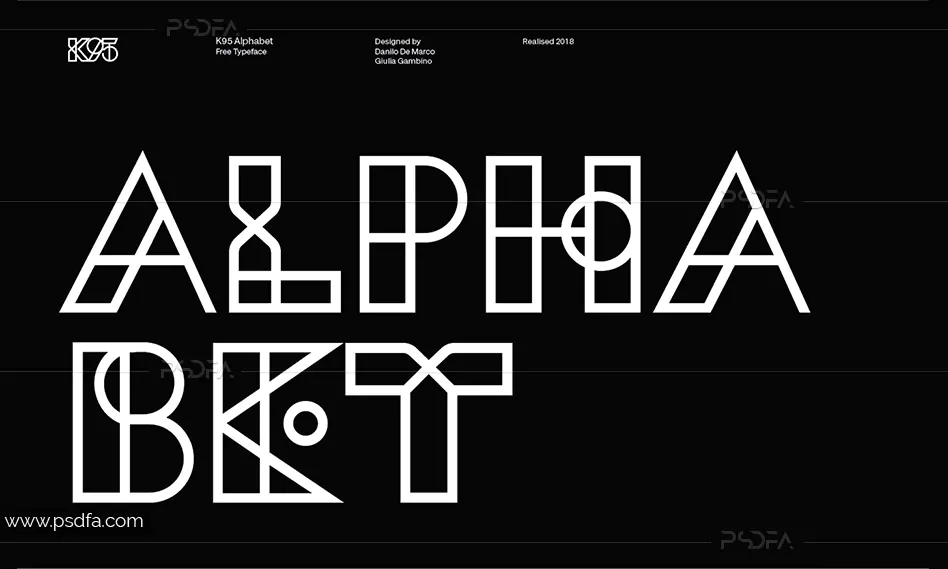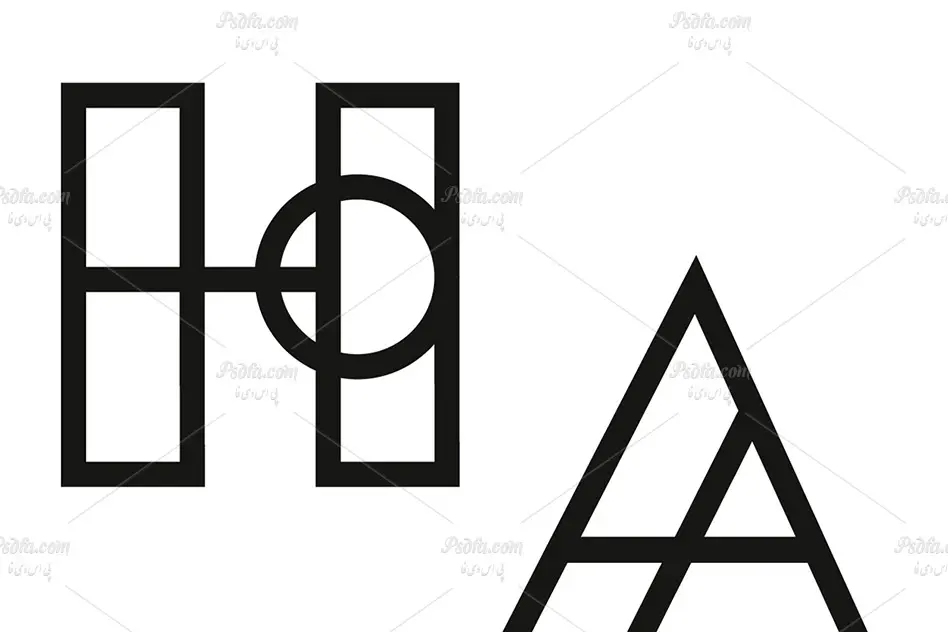
فونت انگلیسی طرح دار K95 Alphabet مناسب برای طراحی
فونت انگلیسی طرح دار K95 Alphabet
در این مطلب شاهد فونت انگلیسی طرح دار K95 Alphabet مناسب جهت استفاده در طرح های گرافیکی به خصوص طراحی انواع پوستر می باشید. این فونت زیبا که به صورت اشکال هندسی طراحی شده است در قالب یک فایل ttf بر روی سایت بارگذاری شده که با نصب این فایل در پوشه فونت های سیستم قادر به استفاده از آن در تمام نرم افزارهای گرافیکی و ویرایشگر متن از جمله نرم افزار فتوشاپ ، افترافکت ، مجموعه نرم افزار آفیس و … خواهید بود. فونت K95 Alphabet در وزن معمولی (Regular) طراحی شده است که می توانید از آن در طراحی انواع طرح های گرافیکی همچون طراحی کارت ویزیت ، تراکت ، بروشور ، بنر ، انواع پوستر و … استفاده کنید.